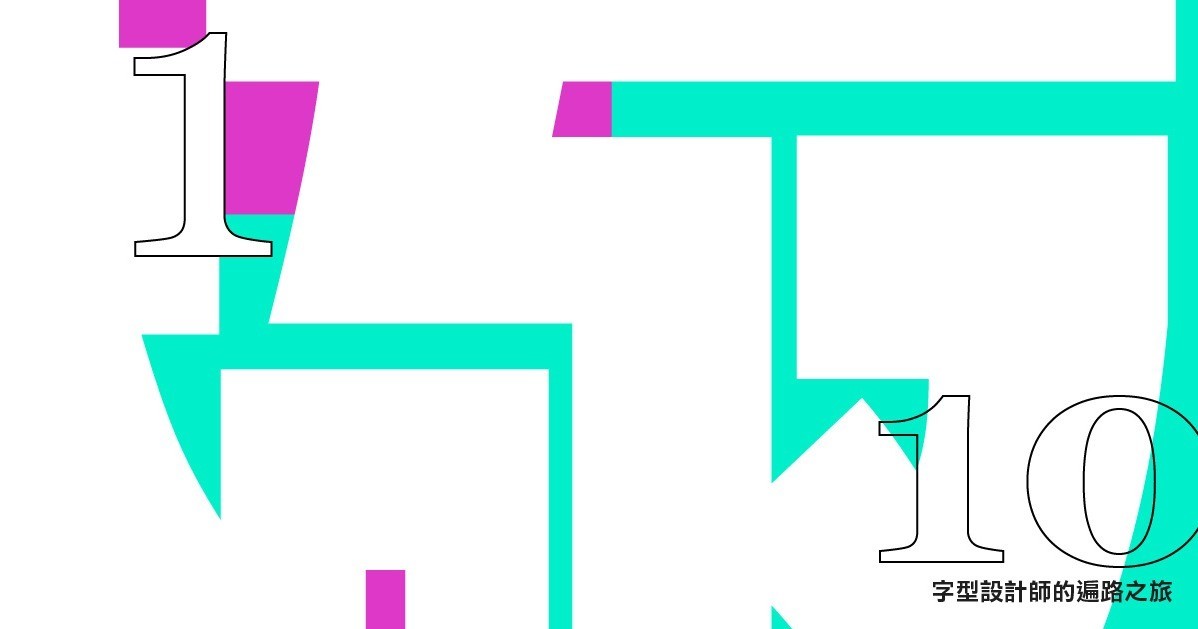
在 1 與 10 之間 — 字型設計師的遍路之旅
justfont 2019 年底的深度交流
在 1 與 10 之間
— 字型設計師的遍路之旅 —
上半場:經驗分享
— 極細、極粗的字型設計經驗分享 —
遍路,原指四國的行者們,為了開發自身,沿著海岸線每日參拜行走的修行之路。這樣修行的路途,往往是行者自身才知道的秘密之路。像極了字型設計師的修煉,在每日不斷的重複工作中,所經歷的過程和累積的體會,往往是外人很難想像體會的。
累積超過三十年的造字經驗,柯熾堅(Sammy Or)老師帶來最新設計的信黑體 W1 和 W10 ,這兩套字型,會呈現出怎樣的視覺衝擊呢?兩個極端,剛好是字型設計最難的「極」之挑戰,極細、極粗的字型設計過程中,遇到什麼樣的困難?可以帶給我們什麼樣的經驗和建議呢?
下半場:深度的交流
— 和新一代設計師的問與答 —
近幾年在很多人的共同努力下,中文字型這以往神秘不受重視的行業,逐漸被大眾所熟悉,也陸續出現新一代的字型設計師們,這些設計師們對中文字型設計充滿熱情,也有許多的創意和想法,但字型設計是條漫長的道路,該如何走下去?中間會遇到什麼樣的困難?前輩們能提出什麼樣的幫助和建議呢?
我們希望藉由這場交流活動,分享中文字型設計的精神與點滴,也因此,這場活動我們特地邀請有字型設計經驗的設計師們,提出他們無論是在技術面、市場面、甚至是心理調適的問題,統一由主持人整理後,成為下半場精彩的對談與討論。
一起參與這場交流的包括金萱、凝書體、淚體、激燃體、日日新、胖皮體、尖剛明體、兵體等新字型的設計師們,都將會一起加入討論並參與這場活動!
講者:柯熾堅(Sammy Or)
三十年以上的中文造字經驗,知名作品包含目前仍能看到的蘋果儷黑、儷宋,在日本熱銷的華康瘦金體、超明體、以及最新力作信黑體等,柯老師也是第一個設計出中文向量字體的人,在目前的中文字體設計中,處處可見到他帶來的影響,例如於擔任華康設計總監期間,決定了許多中文的排版規範,至今仍為中文設計圭臬。。